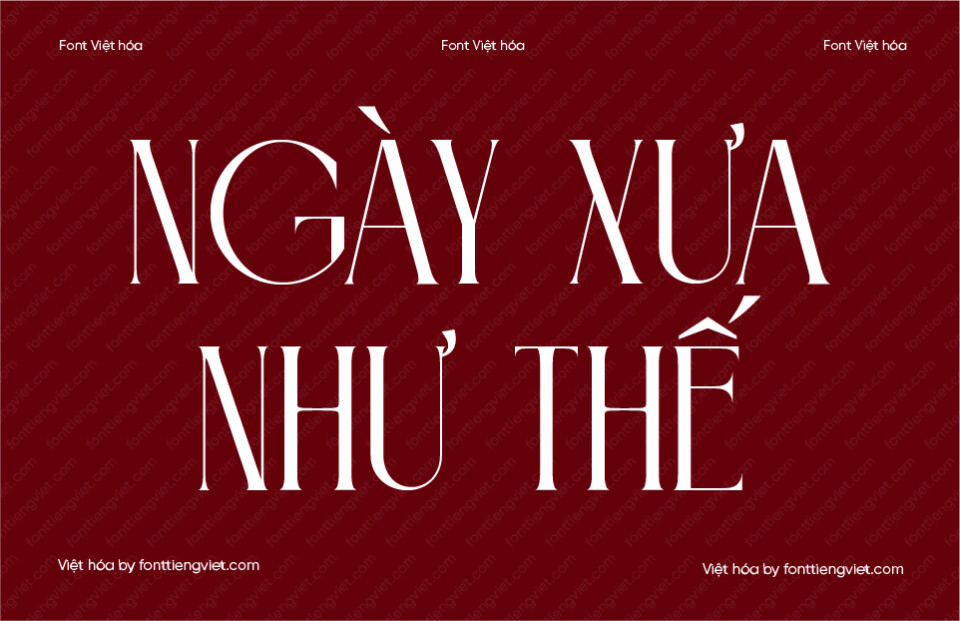
Font Việt hóa 1FTV VIP Glasvia – Sự lựa chọn hiện đại cho thiết kế thẩm mỹ và bao bì
Giới thiệu về Font Việt hóa 1FTV VIP Glasvia – Sự lựa chọn hiện đại cho thiết kế thẩm mỹ và bao bì
Trong thế giới sáng tạo ngày nay, việc lựa chọn một Font Miễn Phí phù hợp đóng vai trò then chốt trong việc truyền tải thông điệp thương hiệu. Font Việt hóa 1FTV VIP Glasvia – Sự lựa chọn hiện đại cho thiết kế thẩm mỹ và bao bì nổi lên như một giải pháp hoàn hảo cho những nhà thiết kế đang tìm kiếm sự kết hợp giữa vẻ đẹp đương đại và tính ứng dụng cao. Được tinh chỉnh kỹ lưỡng về dấu tiếng Việt, bộ font này đảm bảo sự mượt mà và đồng nhất trên mọi nền tảng kỹ thuật số cũng như in ấn truyền thống.
Đặc điểm nổi bật của bộ Font Việt hóa 1FTV VIP Glasvia
Thiết kế sang trọng và đường nét thanh thoát
Đặc trưng lớn nhất của Font Việt hóa 1FTV VIP Glasvia – Sự lựa chọn hiện đại cho thiết kế thẩm mỹ và bao bì chính là các đường nét hình học tinh tế. Các ký tự được xây dựng dựa trên sự cân bằng giữa các khoảng hở và nét đậm nhạt, tạo nên một cảm giác thoáng đãng và dễ đọc. Điều này cực kỳ quan trọng đối với các dự án đòi hỏi sự chuyên nghiệp và phong cách tối giản. Với bộ font này, mỗi con chữ không chỉ là văn bản mà còn là một tác phẩm nghệ thuật đồ họa thực thụ.
Khả năng hiển thị tối ưu trên nhiều chất liệu
Dù được sử dụng trên màn hình máy tính hay in lên bề mặt bao bì giấy, Font Việt hóa 1FTV VIP Glasvia vẫn giữ nguyên được độ sắc nét. Sự linh hoạt này giúp các nhà thiết kế tự tin áp dụng vào nhiều hạng mục khác nhau từ nhận diện thương hiệu đến quảng cáo ngoài trời. Đặc biệt, các dấu câu tiếng Việt được thiết kế hài hòa, không gây cảm giác rời rạc hay làm hỏng cấu trúc tổng thể của từ ngữ, giúp nội dung truyền tải trở nên chuyên nghiệp hơn bao giờ hết.
Ứng dụng thực tế của Font Việt hóa 1FTV VIP Glasvia trong ngành sáng tạo
Sáng tạo bao bì sản phẩm cao cấp
Ngành công nghiệp bao bì luôn đòi hỏi sự đổi mới để thu hút khách hàng từ cái nhìn đầu tiên. Font Việt hóa 1FTV VIP Glasvia – Sự lựa chọn hiện đại cho thiết kế thẩm mỹ và bao bì rất phù hợp cho các dòng sản phẩm làm đẹp, thời trang hoặc thực phẩm bảo vệ sức khỏe. Sự thanh lịch của font chữ giúp nâng tầm giá trị sản phẩm, tạo nên một vẻ ngoài đắt tiền và đáng tin cậy. Khi kết hợp với các tông màu trung tính, bộ font này thực sự tỏa sáng và tạo ra dấu ấn riêng biệt.
Thiết kế poster và ấn phẩm truyền thông
Đối với các bạn học sinh hay sinh viên chuyên ngành đồ họa, việc sử dụng font chữ này trong các bài tập thiết kế poster hay dàn trang tạp chí sẽ mang lại hiệu ứng thị giác cực tốt. Nó giúp bố cục trang web hoặc tờ rơi trở nên hiện đại, bắt kịp xu hướng toàn cầu. Việc nắm vững cách phối hợp font chữ này với các thành phần hình ảnh khác sẽ là điểm cộng lớn trong quá trình học tập và làm việc sau này tại các đơn vị truyền thông.
Kết luận về giá trị của Font Việt hóa 1FTV VIP Glasvia